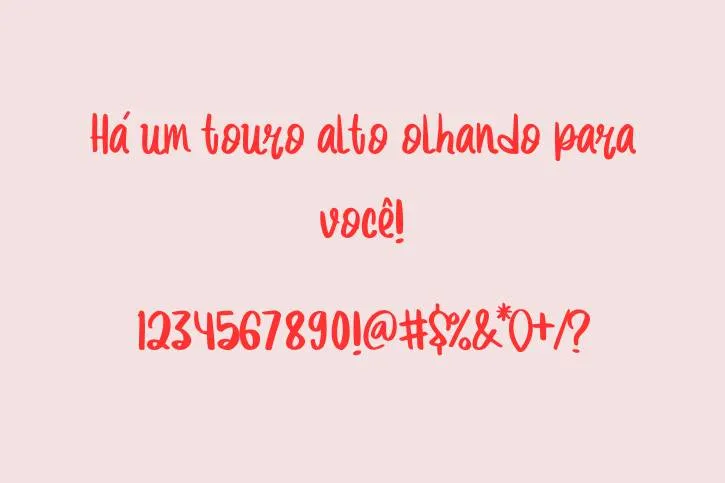
A fonte Miracle of Love é uma fonte manuscrita, desenhada por Booga Letter que evoca uma sensação de autenticidade e calor. Seus personagens são desenhados à mão, o que adiciona um toque pessoal e artesanal a qualquer texto ou desenho. É conhecido pela sua capacidade de transmitir emoções e criar uma ligação emocional com o público.
você pode usá-lo combinando-o com a Fonte AdPro, que tem uma textura semelhante. Com seu visual descontraído e informal, é muito utilizado em projetos que buscam um estilo aconchegante e pessoal. Suas linhas fluidas e levemente inclinadas proporcionam sensação de movimento e dinamismo, sendo ideal para projetos que buscam transmitir sensação de energia e vitalidade.
Além disso, é altamente legível, mesmo em tamanhos menores, tornando-o uma escolha versátil para diversas aplicações. Possui um estilo único e charmoso que agrega um toque de personalidade e aconchego aos seus projetos. Devido à sua natureza manuscrita, pode variar ligeiramente a cada utilização, o que contribui para a sua autenticidade e charme.
Elegância e Sofisticação da Fonte Miracle of Love
É uma tipografia que combina elegância e sofisticação com um toque de delicadeza e charme. Suas linhas suaves e fluidas transmitem sensação de graça e leveza. É uma fonte que adiciona um toque de classe e sofisticação a qualquer design, sem perder o toque caloroso e pessoal.
Você pode usar essa fonte para fins de design mais fantásticos, combinando-a com a fonte Cutesy. Sua aparência manuscrita confere-lhe um caráter único e artesanal, tornando cada palavra e frase visualmente interessante e distinta. Sua elegância sutil e estilo distinto fazem dele uma escolha popular para transmitir uma sensação de beleza e charme.
Usando a Fonte Miracle of Love em Projetos
- Crie logotipos atraentes com um toque único e artístico.
- Aprimore suas postagens de mídia social com a fonte para dar ao seu conteúdo uma aparência personalizada e visualmente atraente.
- Incorpore a fonte em vários projetos artísticos, como citações manuscritas, ilustrações e obras de arte baseadas em tipografia.
- Crie convites personalizados, cartões comemorativos e artigos de papelaria.
- Use a fonte para combiná-la com Fonte IBM Plex Sans para criar pôsteres, folhetos e materiais promocionais.
- Estabeleça uma identidade de marca memorável incorporando a fonte em seus materiais de marca, como cartões de visita e papéis timbrados.
- Use a fonte para criar projetos como presentes personalizados, álbuns de recortes e itens de decoração para casa para adicionar um toque artesanal.
Qual é a fonte da fonte Miracle of Love?
A fonte Miracle of Love é uma fonte manuscrita desenhada por Booga Letter que evoca uma sensação de autenticidade e calor.
Quais são os grandes recursos da fonte Miracle of Love?
Sua melhor característica são os caracteres desenhados à mão, que dão um toque pessoal e artesanal a qualquer texto ou desenho.